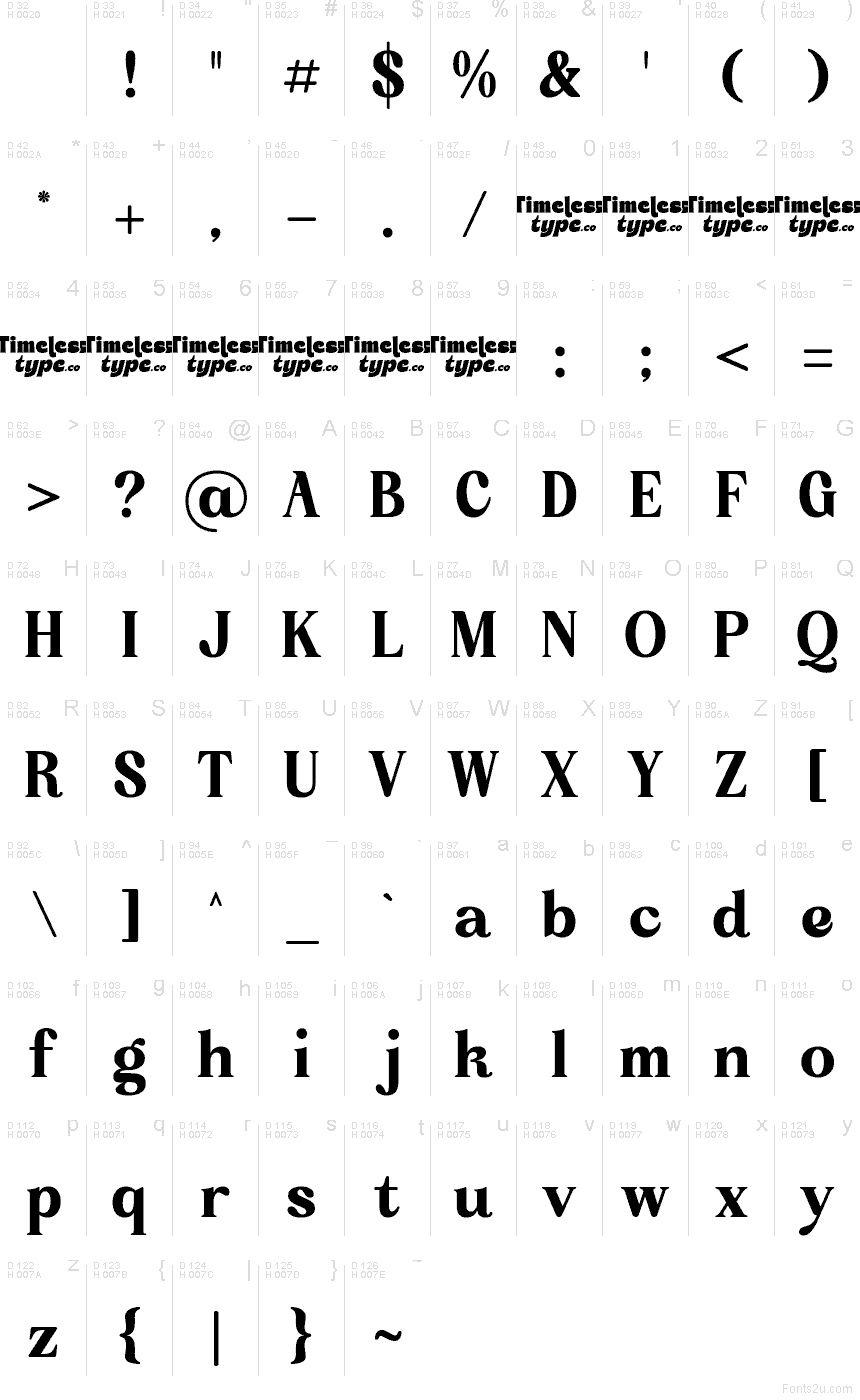
Broken Relent - Decorative Display Serif Font
Eleve a sua visão criativa com a estética marcante de Broken Relent - Decorative Display Serif Font. Esta fonte display experimental funde com maestria referências vintage da Art Nouveau e sofisticação contemporânea, resultando em uma tipografia de alto contraste que atrai olhares instantaneamente. Suas curvas fluidas e expressivas, combinadas a traços imponentes, foram desenvolvidas para conferir elegância artística e requinte a projetos de identidade visual, assegurando que a sua mensagem seja comunicada com personalidade e forte impacto visual.
A versatilidade é um dos pontos fortes de Broken Relent - Decorative Display Serif Font, disponibilizando aos designers um conjunto completo de 430 caracteres e elementos. Com 26 ligaduras exclusivas e 73 alternativas estilísticas, esta fonte viabiliza uma composição tipográfica altamente personalizada. Seja na criação de um logotipo sob medida ou em títulos expressivos, esses recursos decorativos garantem que cada palavra tenha um acabamento artesanal e harmonioso, atendendo aos padrões de projetos profissionais de alto nível.
Amplie seu alcance criativo além das fronteiras com um tipo desenhado para ter impacto internacional. Com amplo suporte a diversos idiomas, Broken Relent - Decorative Display Serif Font se adapta com facilidade aos mercados globais, revelando-se uma ferramenta indispensável para projetos multinacionais. Essa ampla compatibilidade linguística mantém sua identidade visual uniforme e marcante em qualquer país, consolidando a voz da sua marca em um cenário de design cada vez mais integrado.
Perfeitamente indicada para produções de luxo, Broken Relent - Decorative Display Serif Font é a escolha certeira para embalagens premium, design editorial de moda e campanhas publicitárias sofisticadas. É ideal para desenvolver identidades visuais memoráveis, capas de livros refinadas e convites exclusivos para eventos que pedem uma abordagem artística e audaciosa. Transforme suas criações impressas e digitais em peças emblemáticas integrando a elegância atemporal e o dinamismo desta fonte display excepcional.